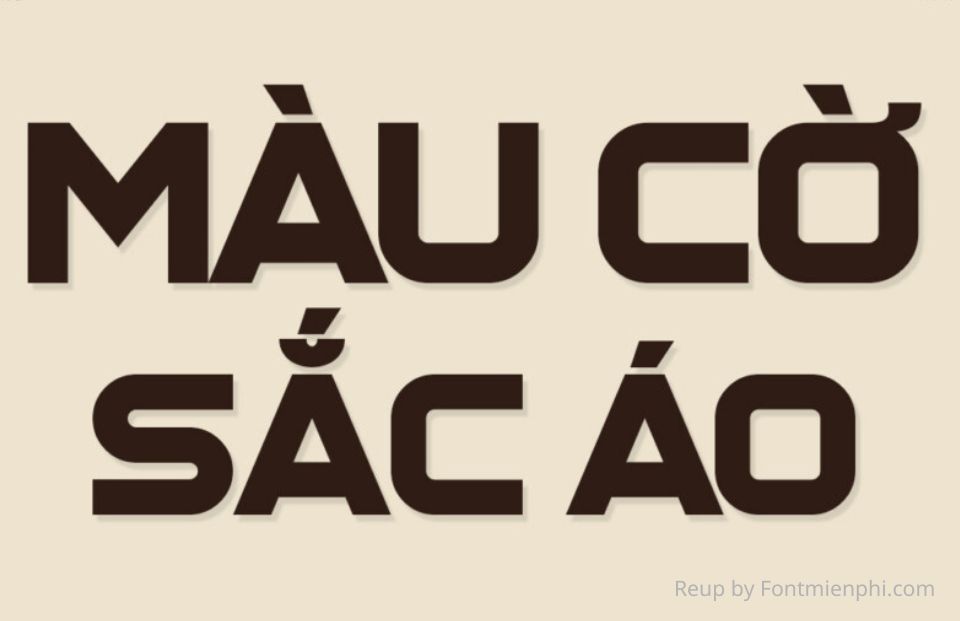
Font Việt hóa 1FTV VIP Relidux – Font chữ cá tính, hiện đại và nổi bật
Font Việt hóa 1FTV VIP Relidux là mẫu font sở hữu phong cách hiện đại, cá tính và có khả năng tạo điểm nhấn mạnh cho các thiết kế sáng tạo. Font phù hợp với nhiều nhu cầu như thiết kế poster, banner, logo, tiêu đề, hình ảnh mạng xã hội, thumbnail, bao bì sản phẩm và các ấn phẩm quảng cáo.
Đặc điểm nổi bật của 1FTV VIP Relidux
Font có đường nét nổi bật, dễ tạo ấn tượng ngay từ phần tiêu đề. Kiểu chữ phù hợp với các thiết kế cần sự trẻ trung, mạnh mẽ và khác biệt. Relidux có thể kết hợp tốt cùng những font sans-serif đơn giản để tạo bố cục cân bằng, chuyên nghiệp hơn.
Bạn có thể sử dụng Font Việt hóa 1FTV VIP Relidux cho:
• Thiết kế logo và nhận diện thương hiệu
• Poster, banner quảng cáo
• Thumbnail YouTube, Facebook, TikTok
• Tiêu đề website và bài đăng mạng xã hội
• Bao bì, tem nhãn sản phẩm
• Thiệp, quote và các sản phẩm thiết kế sáng tạo
Nếu bạn đang tìm kiếm một mẫu font Việt hóa đẹp, cá tính và dễ ứng dụng, 1FTV VIP Relidux là lựa chọn đáng để bổ sung vào bộ sưu tập font thiết kế.